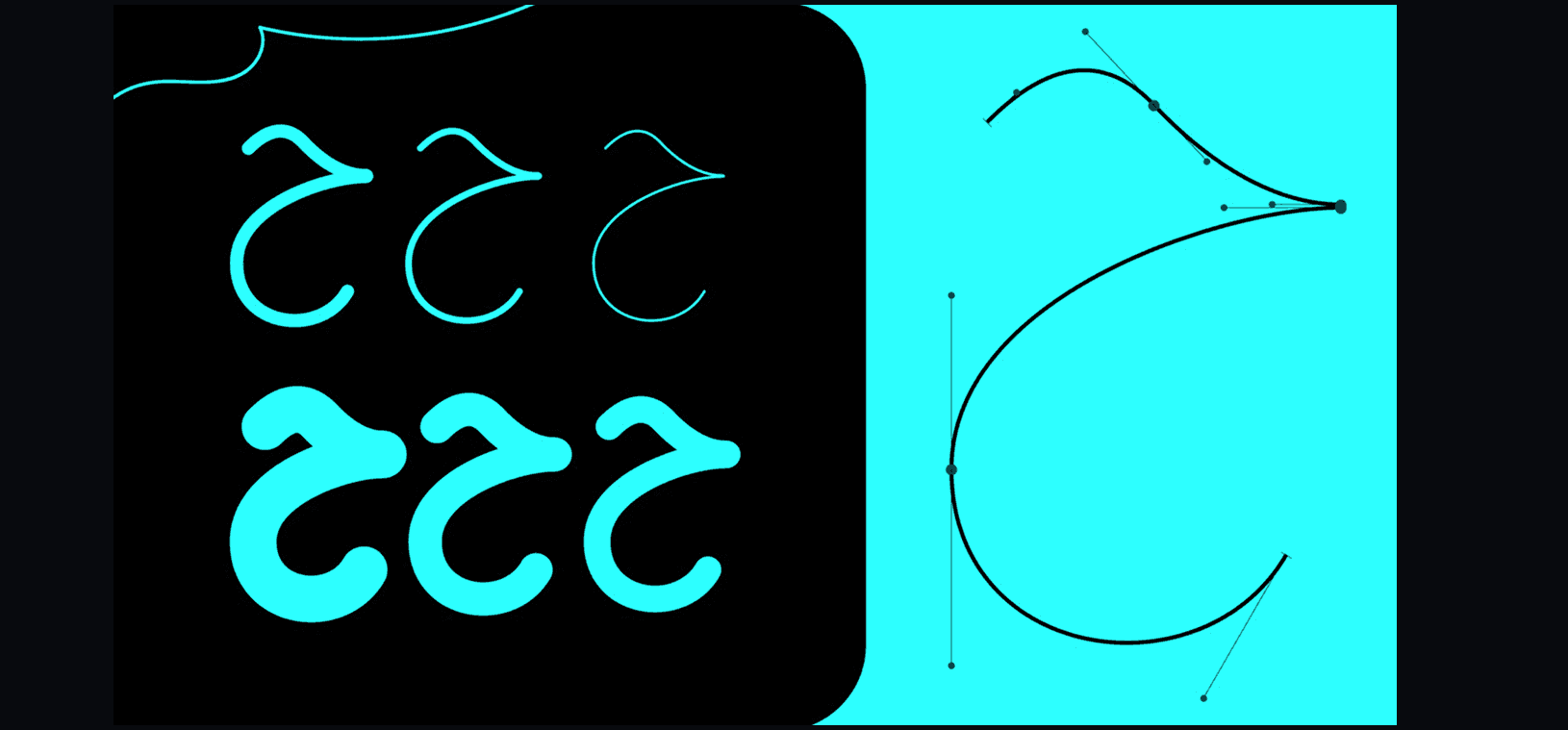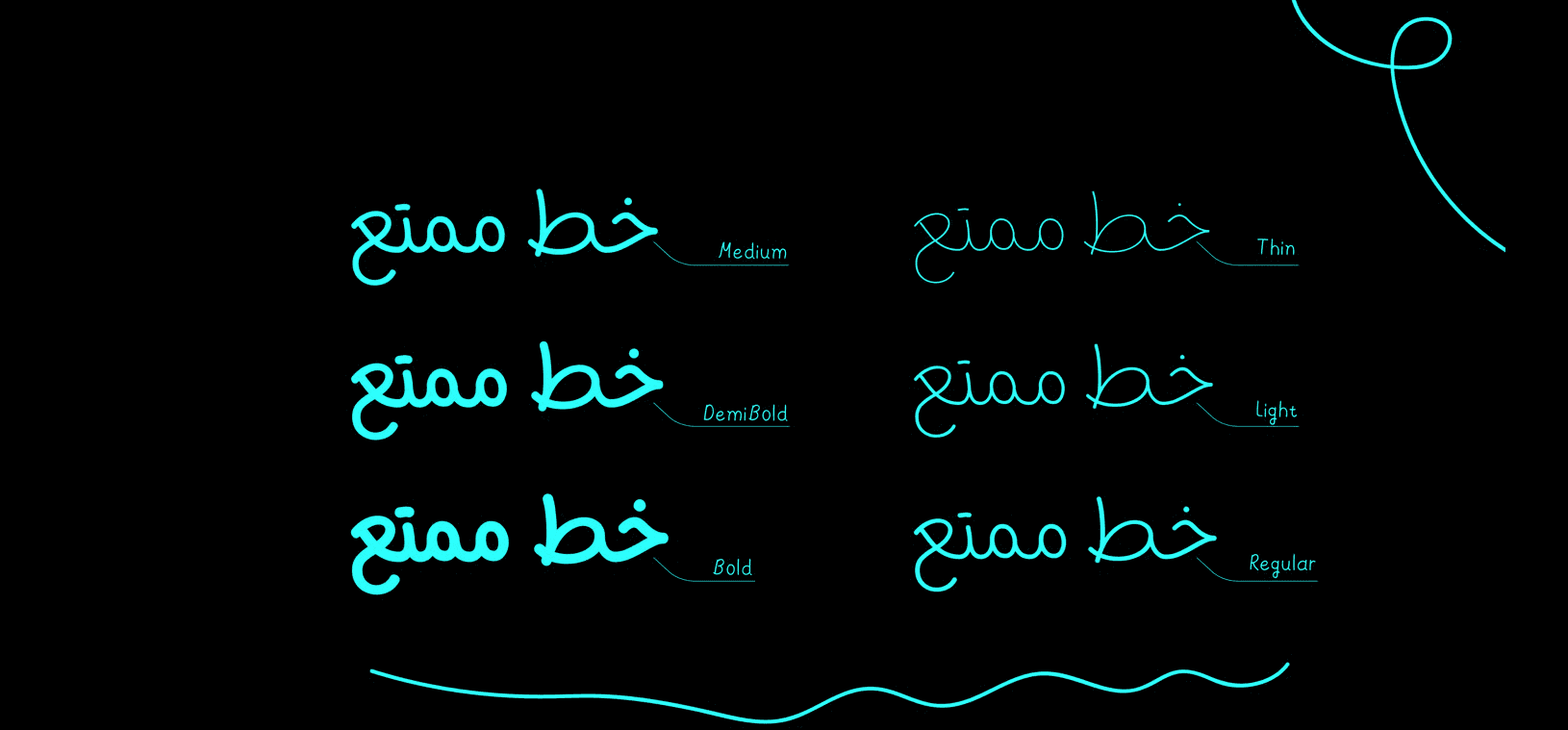
يأتي خط رزان بتصميم عصري مفعم بالحيوية، يتميز بحروفه المنحنية والبسيطة التي تضيف لمسة مرحة وأنيقة في الوقت نفسه. يدعم الخط اللغتين العربية واللاتينية، مما يجعله مناسبًا لتصاميم العلامات التجارية، العناوين الشبابية، والمحتوى الإبداعي على وسائل التواصل الاجتماعي. مثالي للمشاريع التي تتطلب خطًا مميزًا يعكس طابعًا غير رسمي وقريب من القلب.